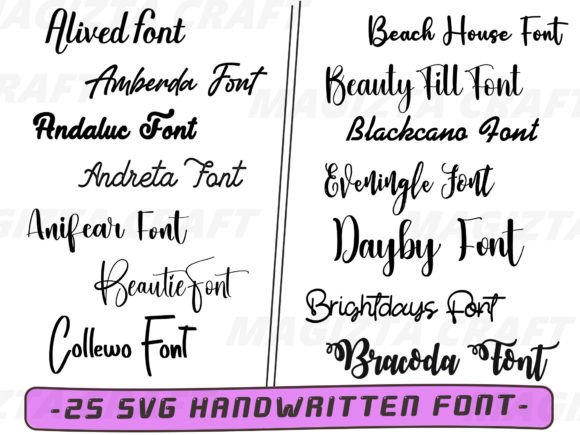
SVG Font Handwritten and Letters
Encontrar los elementos de diseño adecuados puede ser un desafío, pero SVG Font Handwritten and Letters ofrece una colección excepcional que eleva tu trabajo al instante.
Elaborado con precisión, SVG Font Handwritten and Letters proporciona vectores limpios, tipografía suave y una licencia comercial para tu tranquilidad.